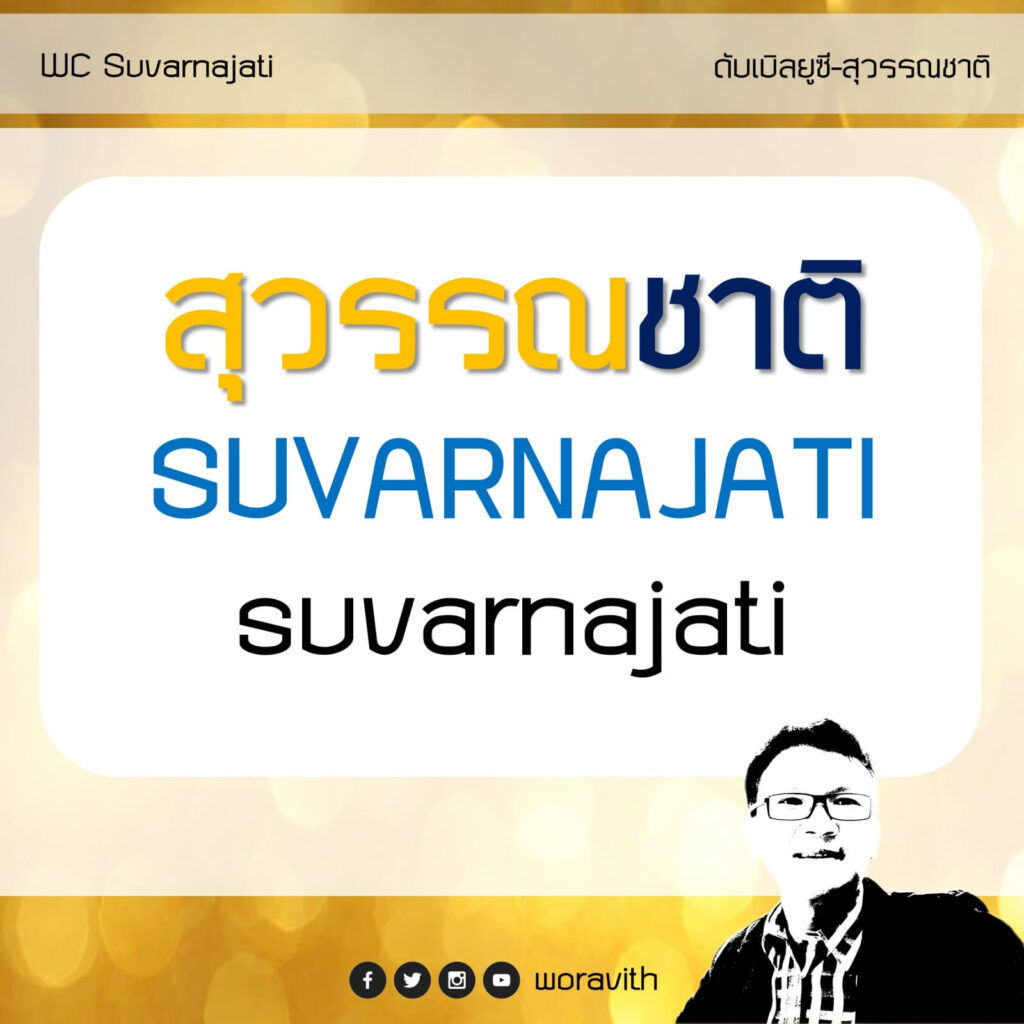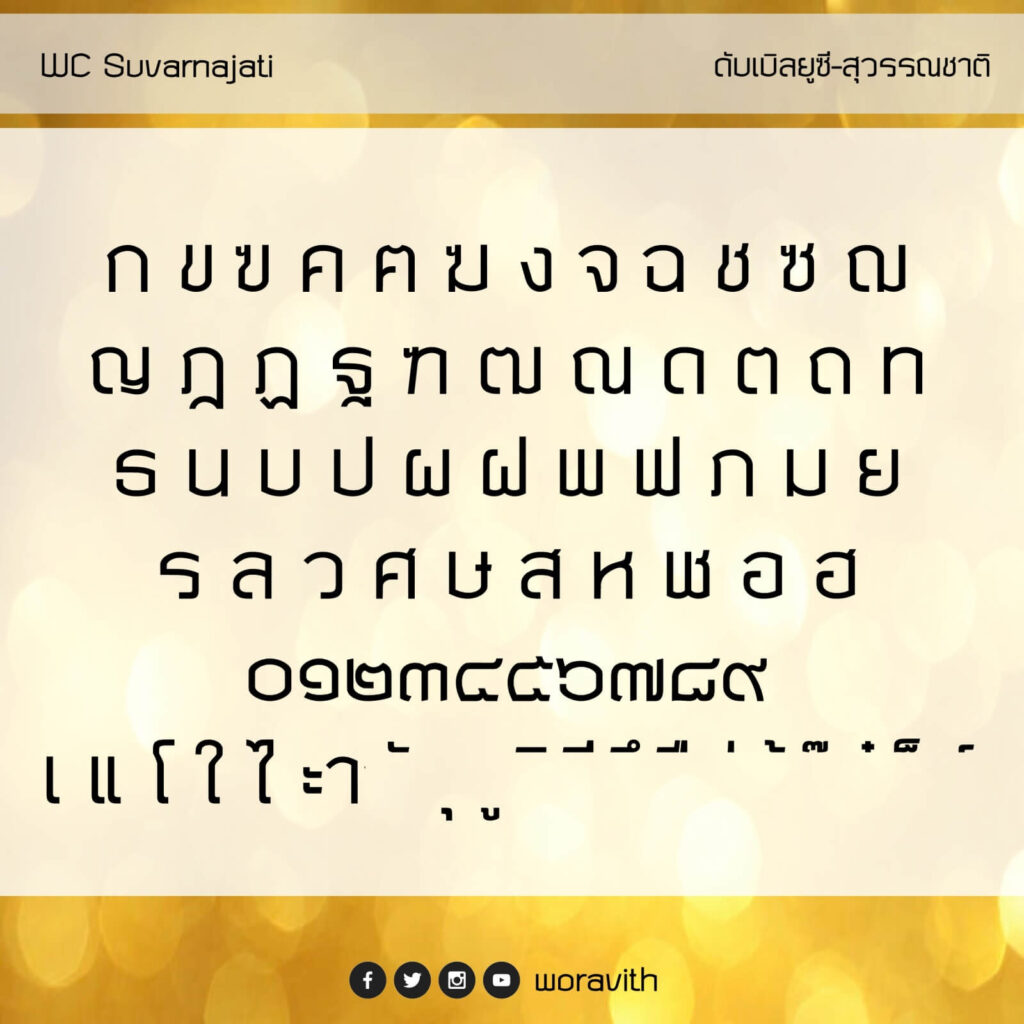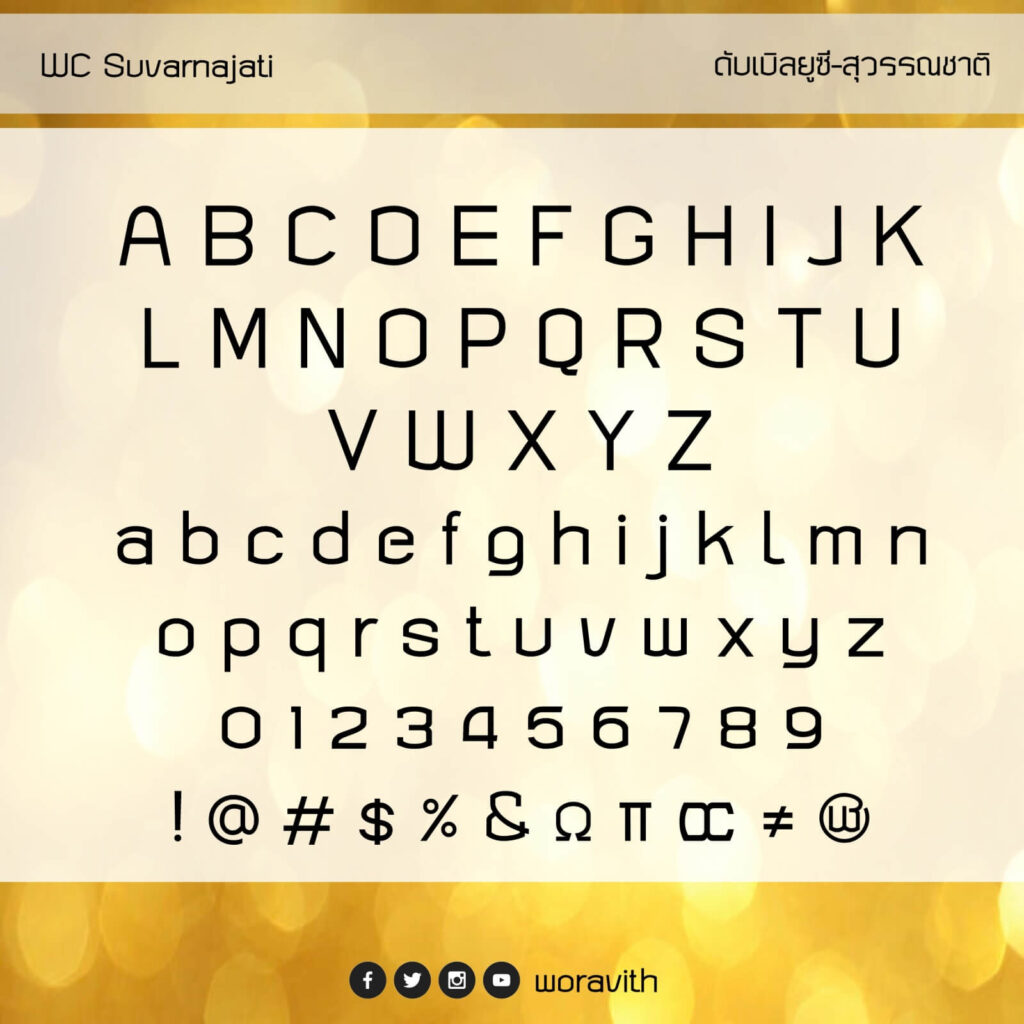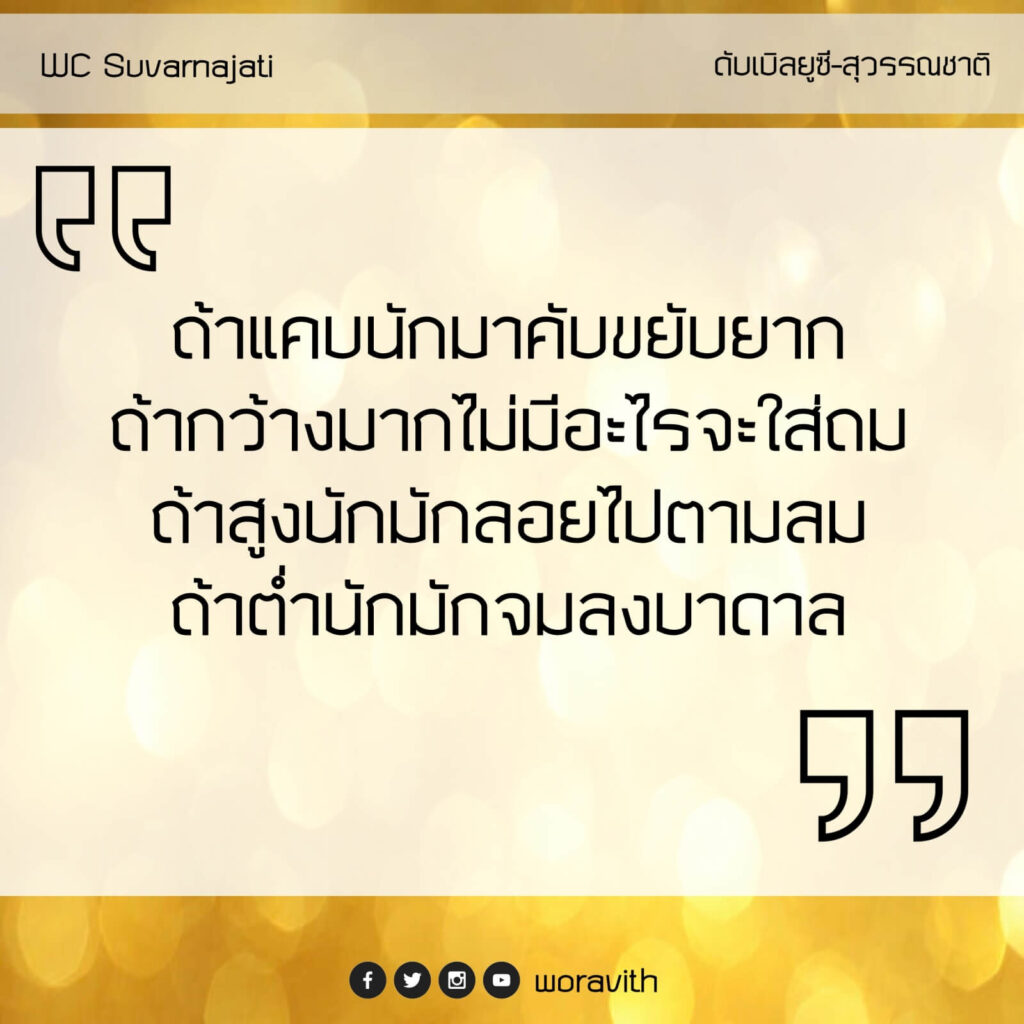
ฟอนต์สุวรรณชาติพัฒนาจากรูปวงรี ผสมผสานกับแนวเส้นตรง แสดงความเข้มแข็ง แต่ก็มีส่วนโค้งให้อารมณ์ดูผ่อนคลายบ้าง
ผู้สร้างสรรค์ : วรวิทย์ จันทร์สุวรรณ (Woravith Chansuvarn)
ดับเบิลยูซี สุวรรณชาติ (WC Suvarnajati)